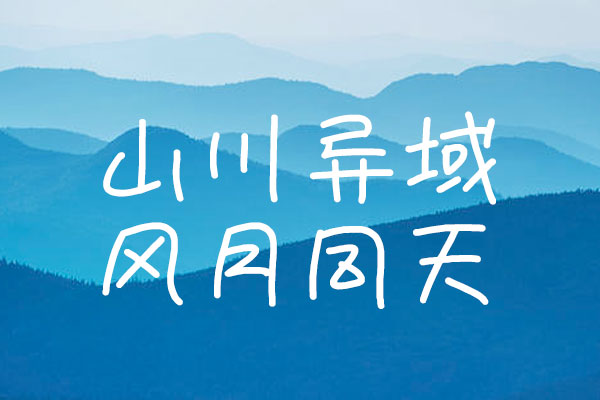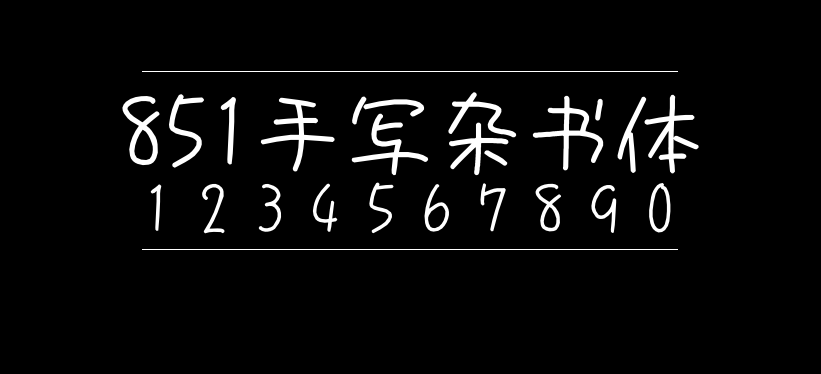
字体下载 851手写杂书体
851手写杂书体
851手写杂书体(851tegakizatsu 、 851手書き雑フォント)是日本设计师手写的一款字体,很像是一般人用原子笔书写一般。不过值得推荐的是,这一款手写字体包含了中文字相对来说是比较完整的,所以使用起来还是爽的!
作为一款可爱风的手写字体,虽为日文字体,但对中文繁体以及中文简体都支持得灰常不错,真是意外的惊喜!
这款字体包含3万多文字字符,还在不断更新中。